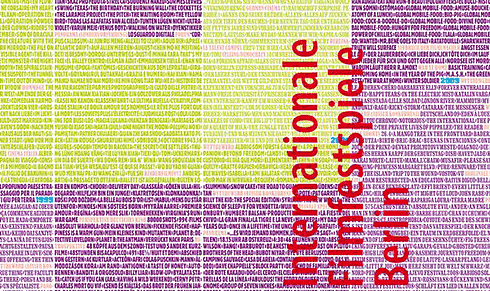
Es ist Tradition im Fontblog, alle Jahre wieder einen ausführlicheren Blick auf das Plakat des Berliner Filmfestspiele Berlinale zu werfen. Vor wenigen Stunden wurde das Plakat 2010 vorgestellt, entworfen vom Neuköllner Büro Otto Sauhaus (Michael Fröhlich, Sarah Lamparter, Karl Zech). Das in der Berliner Szene gut vernetzte Designbüro arbeitet überwiegend für Kunden aus dem Kulturbereich (z. B. Deutsches Theater, Babelsberger Filmgymnasium, Schramm Film, dokumentART, Allgäuer Puppenbühne, Verbrecher Verlag, …) und sieht seine Kompetenz im Bereich Grafik, Illustration und Typografie. Sein Aufgabenbereich umfasst Konzeption, Gestaltung und Produktion in den Medien Druck, Animation, Film und Web. Die Webseite von Büro Otto Sauhaus ist für mich ein konzeptionelle, optischer und technischer Genuss.
Für das Geburtstagsplakat der Berlinale haben die Designer die Titel alle Filme, die seit Beginn des Festivals 1951 gezeigt wurden, zusammengestellt und als Textmuster inszeniert (vgl. vergrößerter Ausschnitt am Beginn dieses Artikels). Rund 15 000 Filmtitel aus aller Welt bilden den Hintergrund und das Vordergrundmotiv des zweifarbigen Entwurfs. Weil auch die Chronologie aller Filme berücksichtigt wurde, werden sicherlich die Augen viele Betrachter bei näherem Hinschauen mit dem Lesen beginnen. Damit, so die Berlinale Leitung, biete das Poster einen ganz besonderen Blick auf die Festivalgeschichte. »Mit etwas Geduld wird jeder seine Lieblingsfilme finden. Mit dieser filmhistorischen Reise möchten wir alle Filmkünstler, deren Filme die Berlinale so besonders machten, noch einmal ehren«, kommentiert Festivaldirektor Dieter Kosslick das Konzept.
Wie schon im Jahr 2009 steht auch in diesem Jahr ein einziges Motiv für die gesamte Berlinale. Auf Sektionsplakate wurde zugunsten einer einheitlichen Kommunikation verzichtet. Ab 26. Januar 2010 wird das Plakat im gesamten Berliner Stadtbild zu sehen sein.
Das Plakat gefällt mir sehr gut und ganz deinem Empfinden nach ist die Homepage vom Büro Otto Sauhaus ein optischer Genuß.
ob sich die titel wiederholen oder wurde jeder nur einmal genannt?
was hat der betrachter davon, dass sich da die 15.000! titeln verstecken? es wirkt nicht nur ein bisschen nach film, eher wie eine design konferenz.
die farbwahl ist natürlich geschmackssache obwohl mehr kontrast wäre bestimmt nicht falsch gewesen, gerade im berliner straßenbild.
ich bin nicht überzeugt und ich mag berlin und liebe filme und typografie.
Man muss ja nicht immer das Rad neu erfinden, klar. Aber Titel nacheinander hinschreiben ist schon ein wirklich alter Hut. Das machen Zweitsemestrige in unserer Klasse. Das eckige “ber–lina–le” hingegen find ich schön. Obwohl die Lina natürlich nichts damit zu tun hat.
welch grausiges plakat. da war das letztjährige ja die goldene palme wert